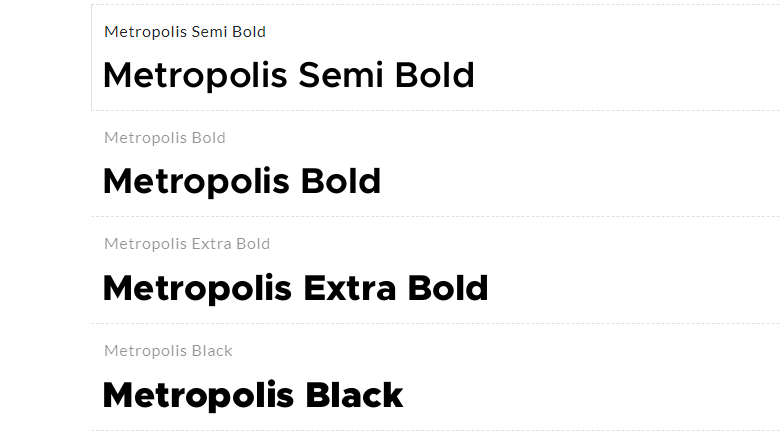
MetroPolis Font Ailesi -Web için Mükemmel Font
Türkçe Font - Gazete - Dergi - Broşür - Webfont olarak kullabilirsiniz.
Karekter temiz tırnaksız yumuşak karekter..
Özellikle semibold çok tatlı duruyor hocam
Font çok güzel
Ben web calismalarinda segui ui ve roboto serilerini kullanıyordum buna denk gelince artık bunu kullancam. Poppinde ç ve ş lerde sikinti var